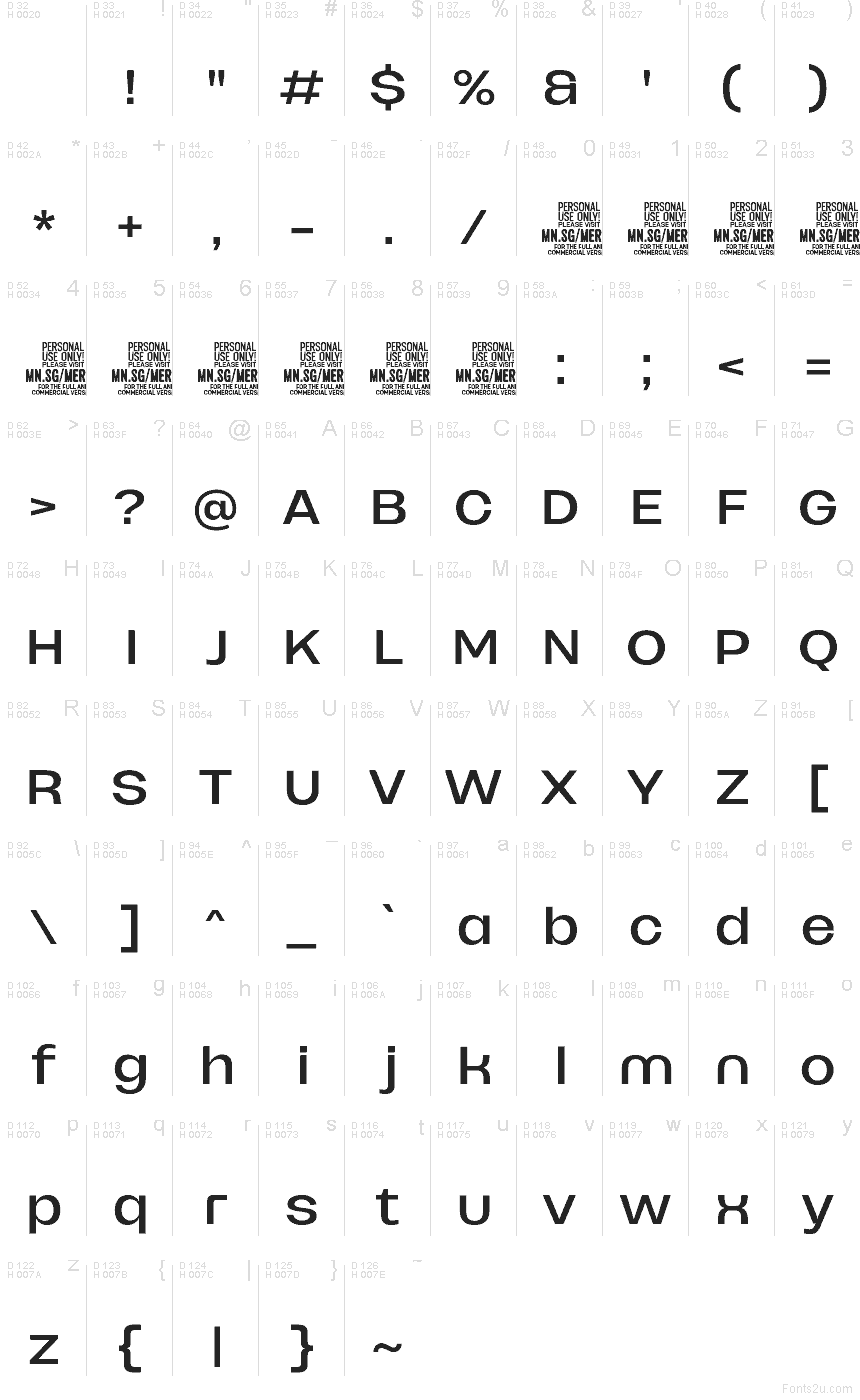
Merica Futurist PERSONAL USE Regular
Merica Futurist, desenvolvida pela Mans Greback AB, é uma tipografia sem serifa futurista e gratuita, com um traço aerodinâmico e marcante. As letras misturam curvas amplas com cantos cortados e ângulos quadrados, conferindo ao design uma estética limpa de ficção científica que parece muito bem estruturada, fugindo do comum.
É perfeita para branding de tecnologia, logotipos de games, títulos em pôsteres, cartões de título e embalagens onde se precisa de uma fonte gratuita com um tom sofisticado e futurista sem perder a funcionalidade. As minúsculas arredondadas garantem um toque de acessibilidade, enquanto os encaixes precisos e as verticais firmes conferem um ar mais cinematográfico a nomes curtos, capas e elementos de interface.